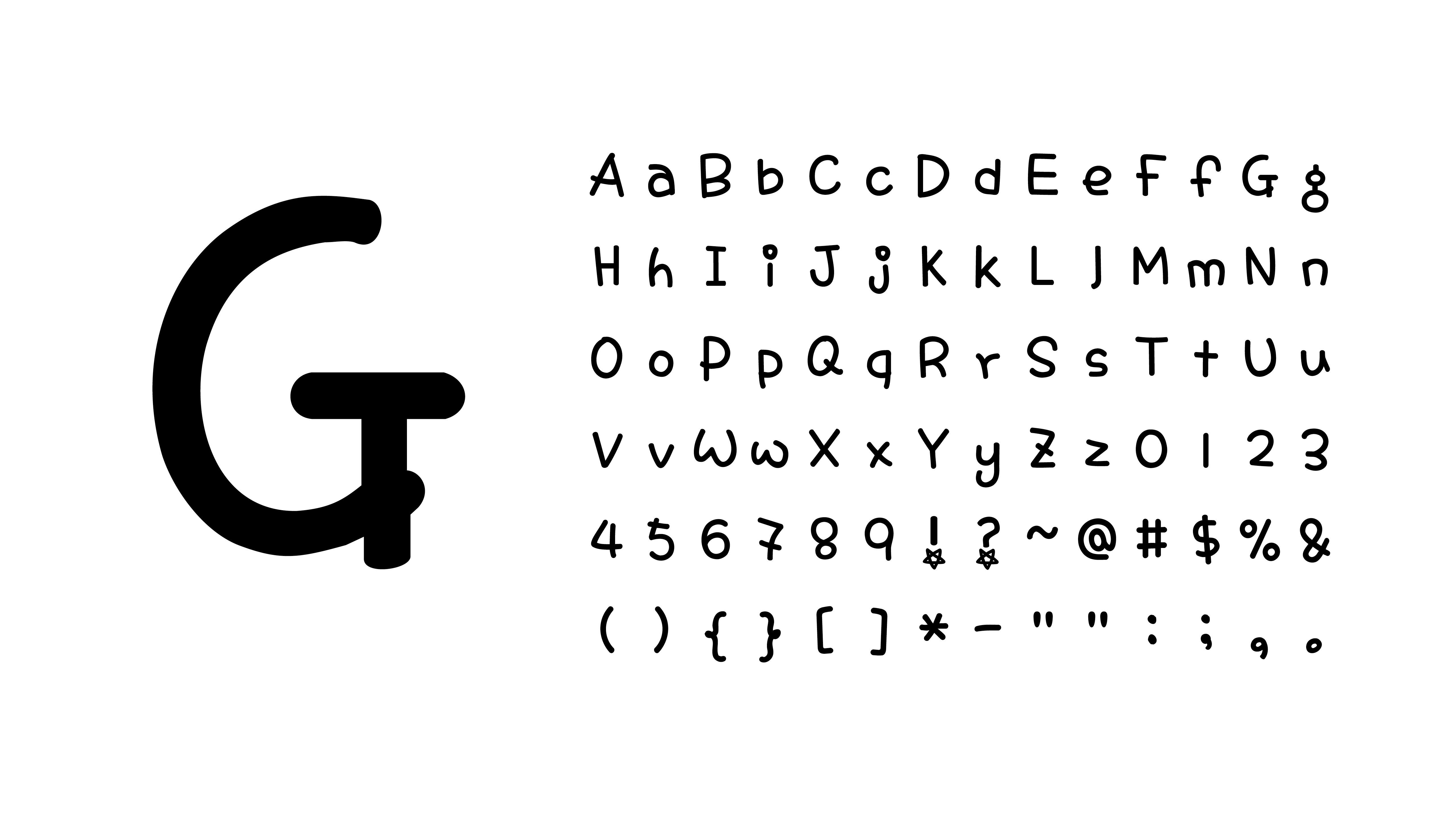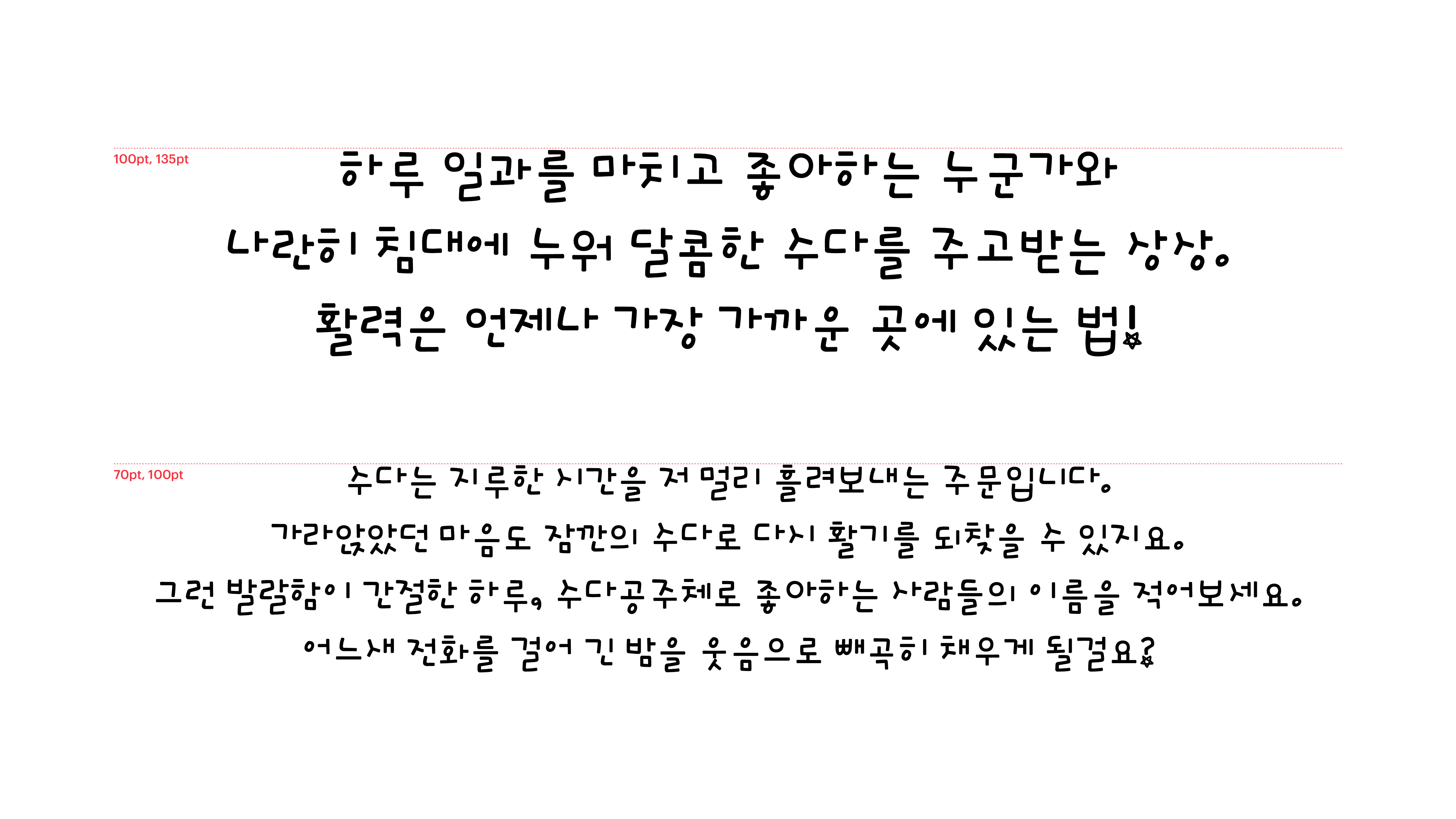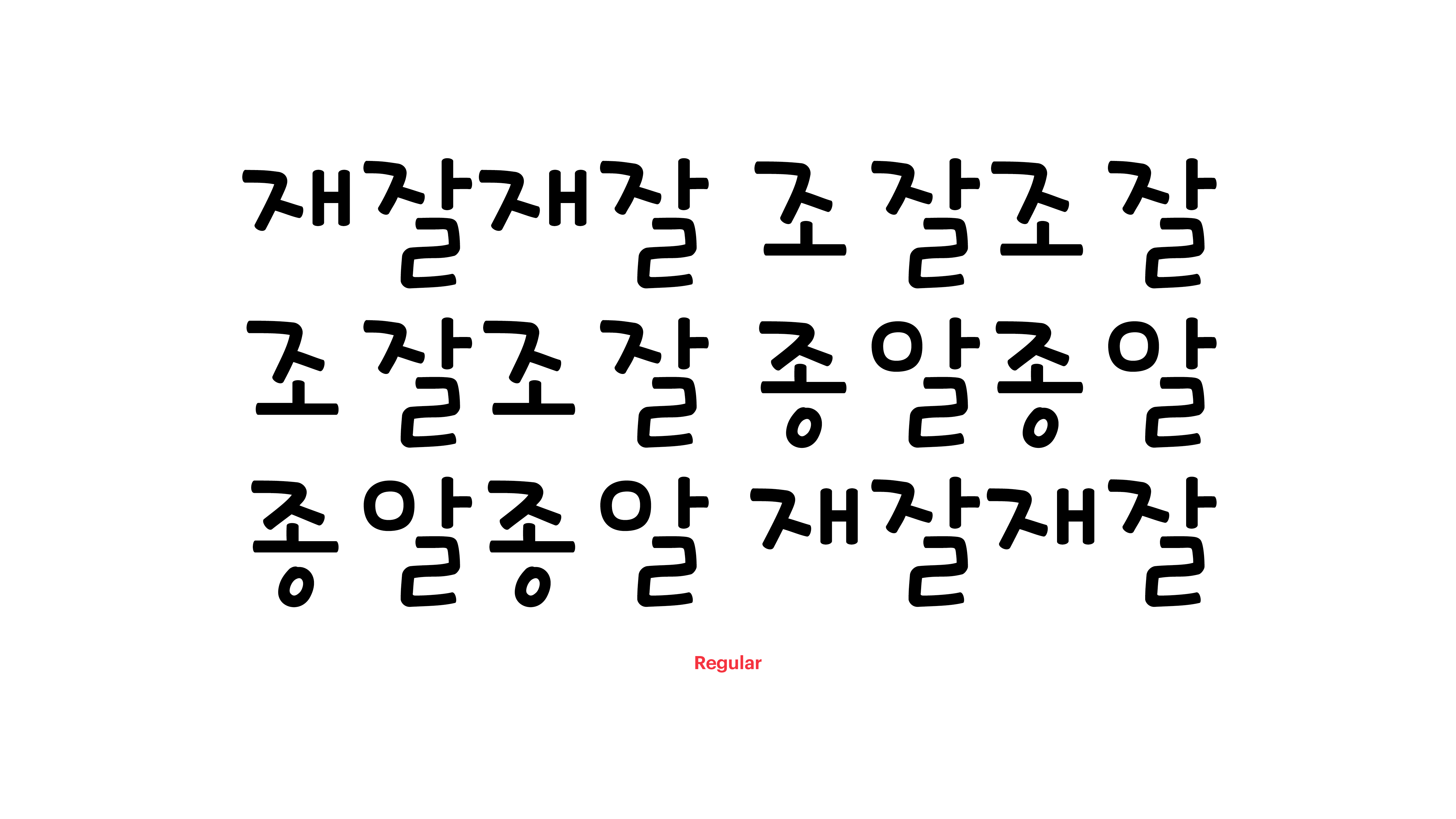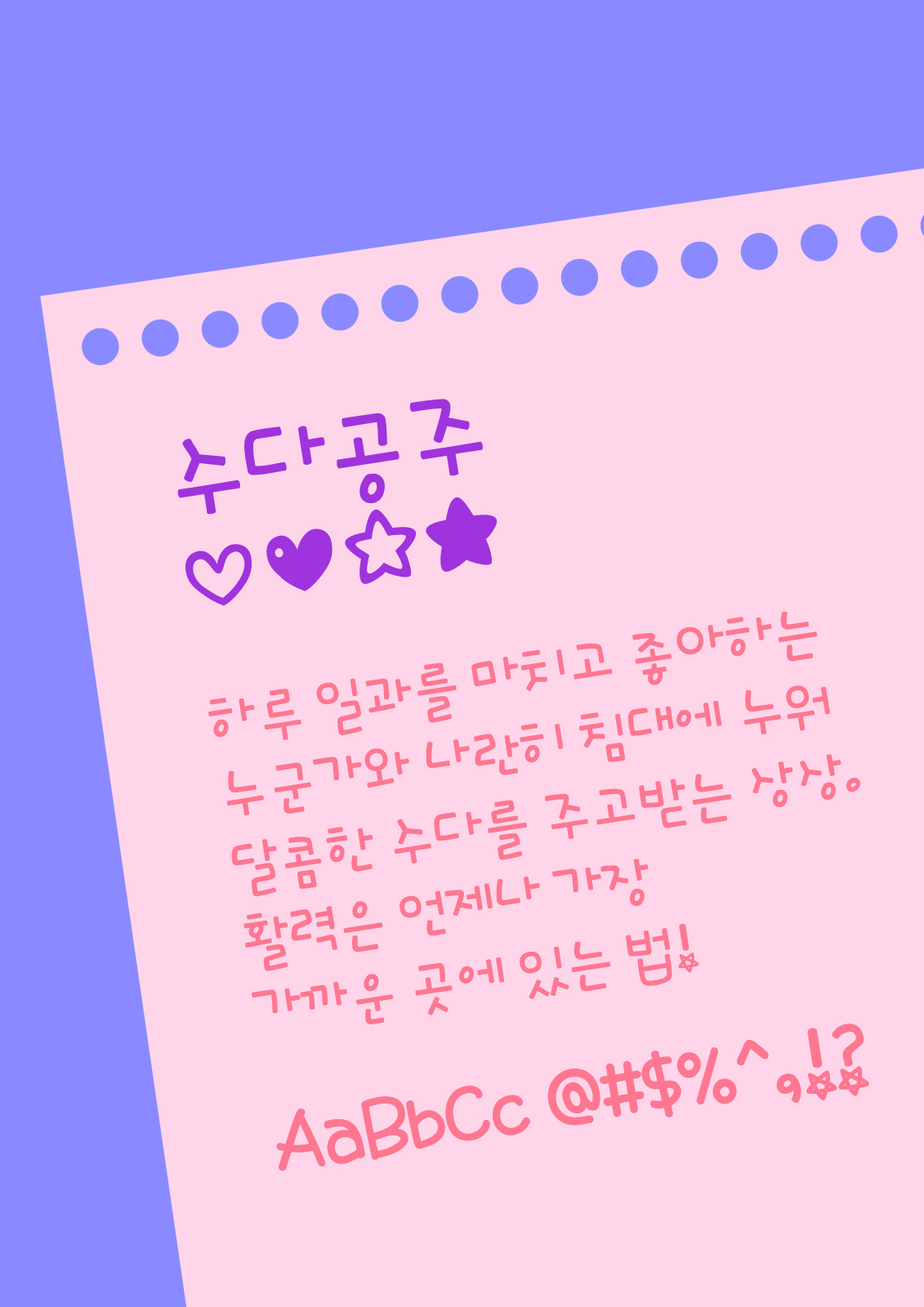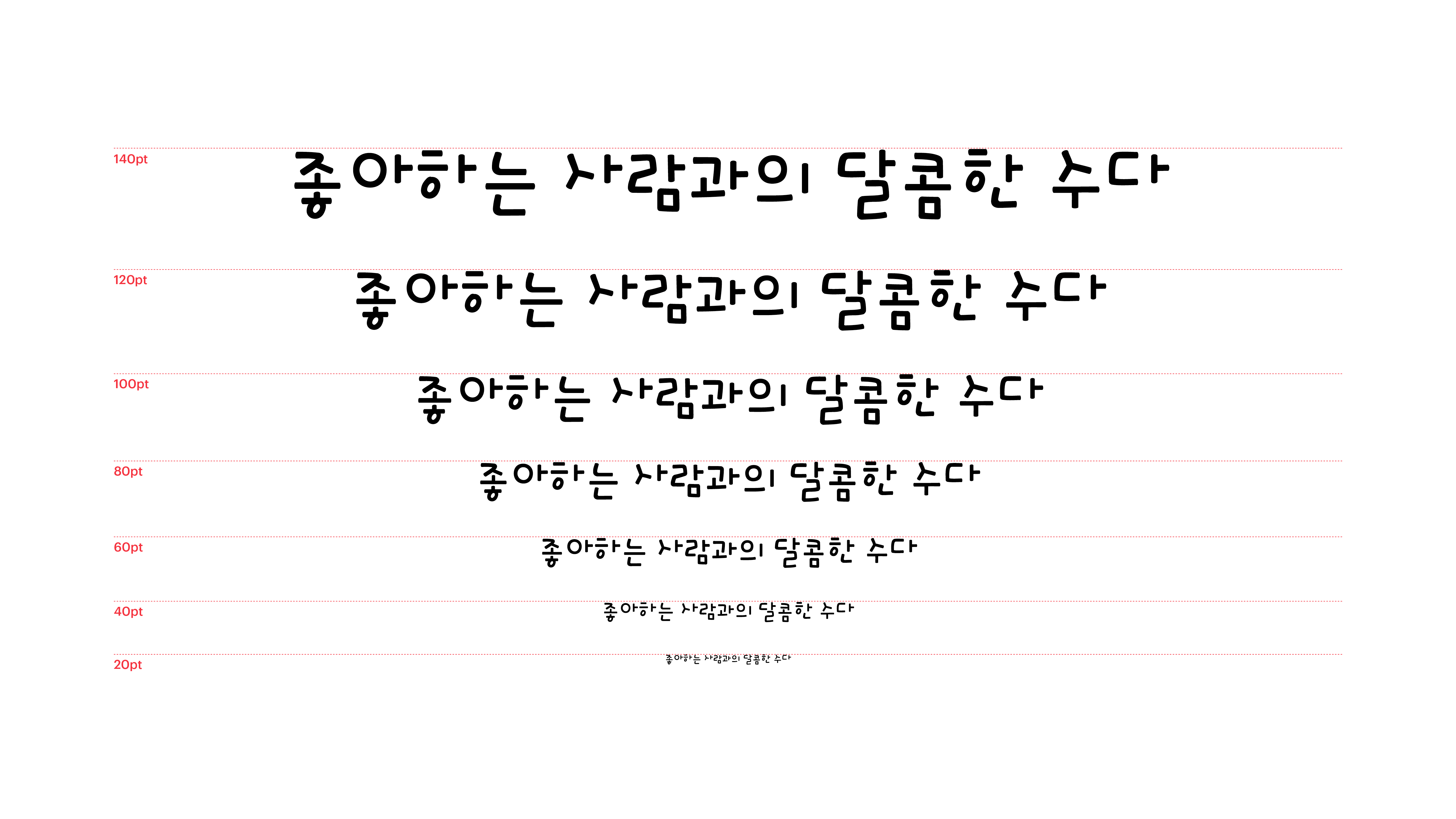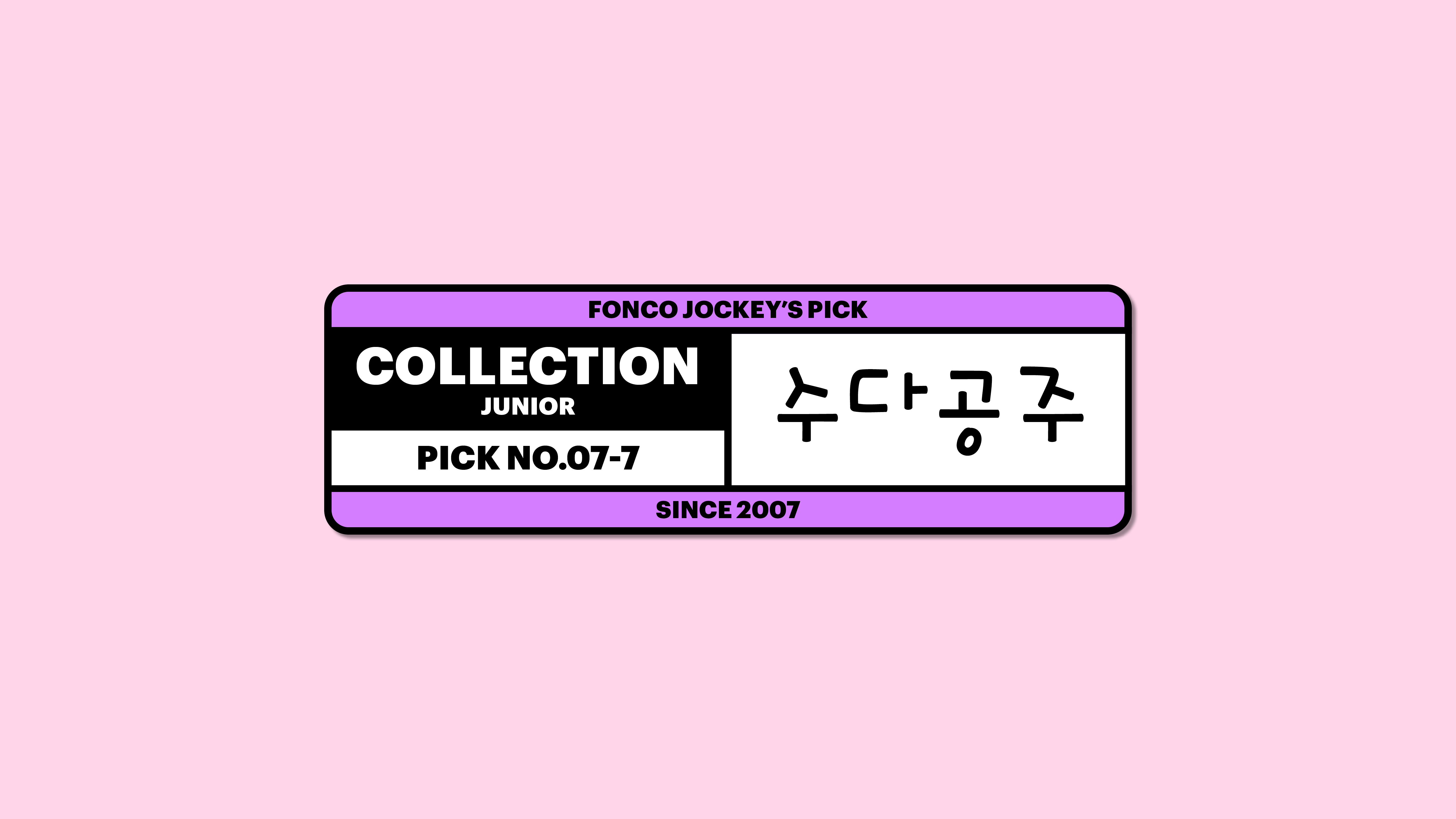
수다공주
Yoon 수다공주
수다는 지루한 시간을 저 멀리 흘려보내는 주문입니다. 가라앉았던 마음도 잠깐의 수다로 다시 활기를 되찾을 수 있지요. 그런 발랄함이 간절한 하루, 수다공주체로 좋아하는 사람들의 이름을 적어보세요. 어느새 전화를 걸어 긴 밤을 웃음으로 빼곡히 채우게 될걸요?